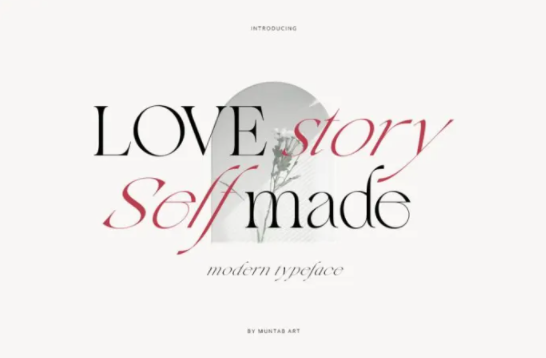
Fontbundles Love Story Self Made Font 2021
[Fontbundles] Love Story Self Made Font (2021)
Шрифт Love Story Self Made включает прописные буквы, строчные буквы, цифры, большой набор знаков препинания.
Шрифт Serif с современным стилем.
Создан для плакатов, веб-дизайна, брендинга, иллюстраций, значков и некоторых других работ.